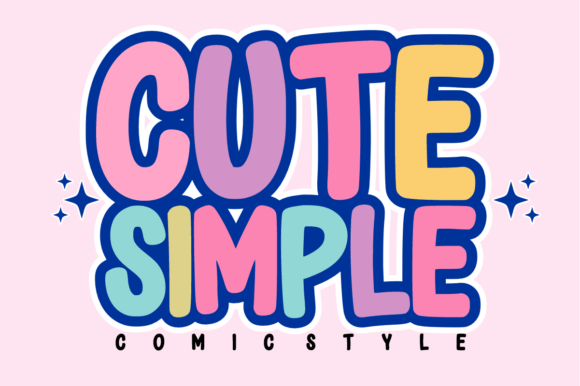
Cute Simple
Cute Simple : la police d’affichage polyvalente qui séduit par sa douceur
Si vous cherchez une police d’affichage à la fois simple et charmante, Cute Simple répond parfaitement à vos attentes. Conçue pour les créateurs qui veulent allier lisibilité, modernité et une touche ludique, cette police devient rapidement l’outil incontournable pour tous vos projets graphiques.
Pourquoi choisir Cute Simple ?
- Design épuré et arrondi : des lettres « chunky » qui offrent une lecture aisée tout en restant adorables.
- Variété de glyphes : alphabet majuscule, chiffres, symboles de base et ponctuation pour une composition complète.
- Optimisée pour le découpage : chaque contour est pensé pour une coupe précise et fluide.
Applications idéales pour Cute Simple
- 🏫 Ressources pédagogiques – affiches de classe, fiches d’exercices, badges nominatifs.
- 👕 Vêtements enfants – t‑shirts, hoodies, bodies avec un style doux et accueillant.
- 🏷️ Étiquettes et stickers – organisation de la maison, planners, décalcomanies personnalisées.
- 🎂 Événements festifs – invitations, banderoles, décorations d’anniversaire.
- 💼 Branding moderne – logos, cartes de visite, supports de communication qui veulent paraître accessibles.
Conclusion
Avec son esthétique sucrée et stylée, Cute Simple se positionne comme la police d’affichage ultime pour tous ceux qui veulent allier professionnalisme et convivialité. Que vous soyez enseignant, créateur de produits personnalisés ou designer freelance, elle vous garantit des résultats nettoyés, lisibles et irrésistiblement mignons.